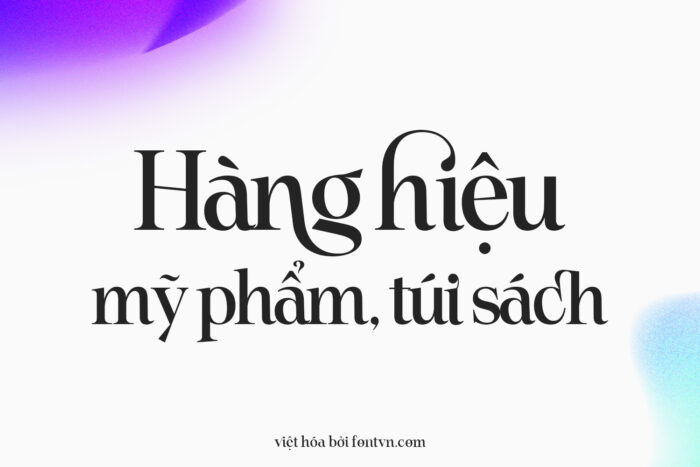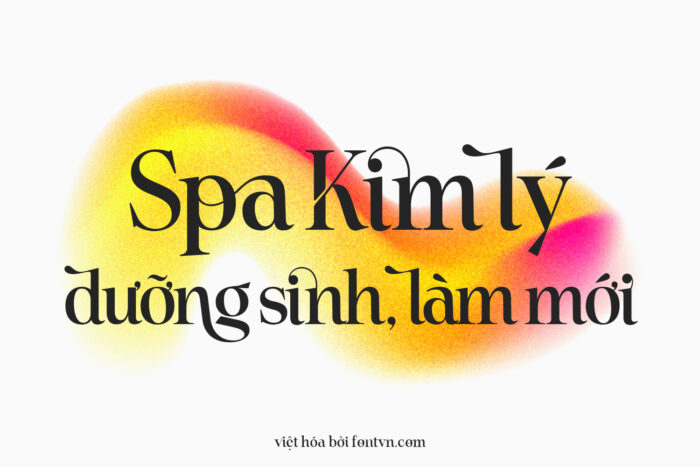
DVN Astera Việt hóa – Font chữ Serif thời thượng phù hợp cho thương hiệu cao cấp
DVN Astera là một font chữ Serif hiện đại, tinh tế được Việt hóa hoàn chỉnh, mang đến sự hoàn hảo cho các thiết kế cao cấp, sang trọng. Với các đường nét thanh mảnh, mềm mại kết hợp với các ligature độc đáo, DVN Astera tạo nên một phong cách chữ viết trang nhã và lịch lãm. Các ký tự của DVN Astera có sự cân đối hài hòa, vừa mang nét cổ điển của Serif vừa có sự phá cách của thời đại mới, giúp dễ dàng thu hút ánh nhìn. Font chữ này không chỉ nổi bật trong các thiết kế thương hiệu, logo, mà còn phù hợp cho các ấn phẩm quảng cáo, bao bì sản phẩm, và thiệp mời. Với sự đa dạng trong ứng dụng và tính thẩm mỹ cao, DVN Astera là lựa chọn lý tưởng cho các thương hiệu mong muốn truyền tải thông điệp sang trọng và đẳng cấp.